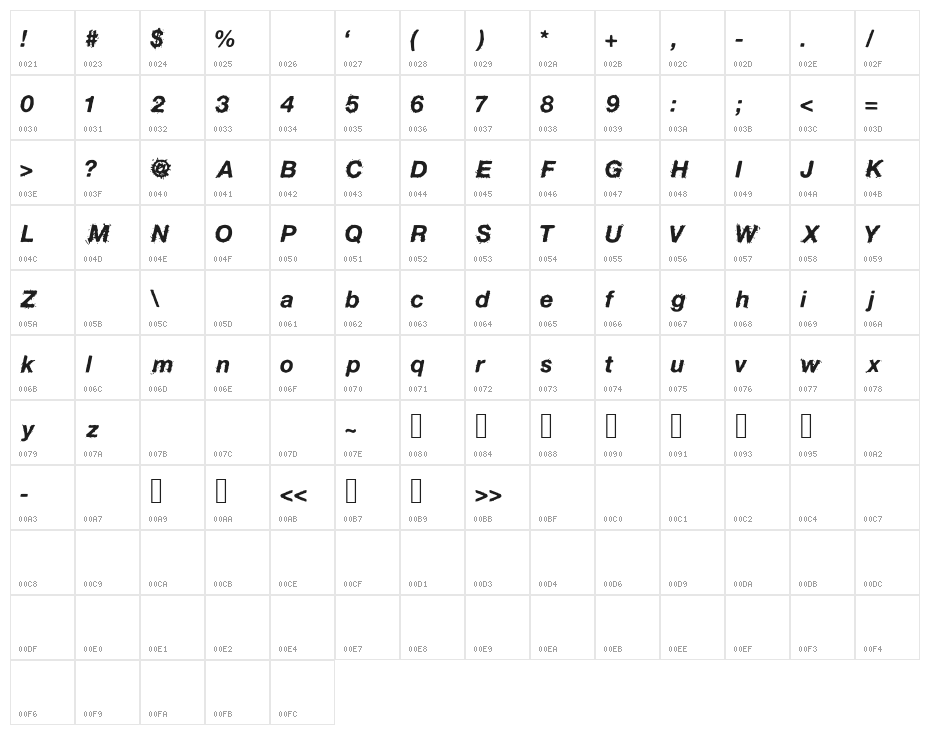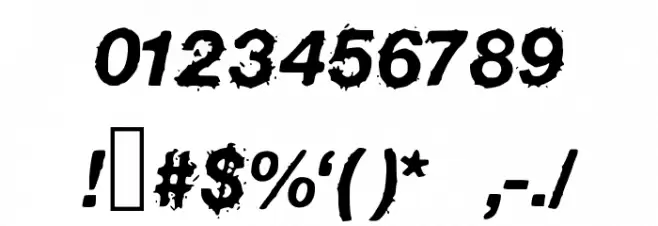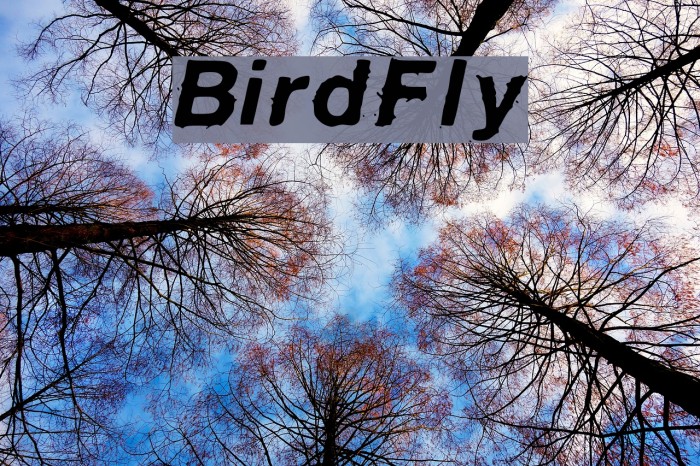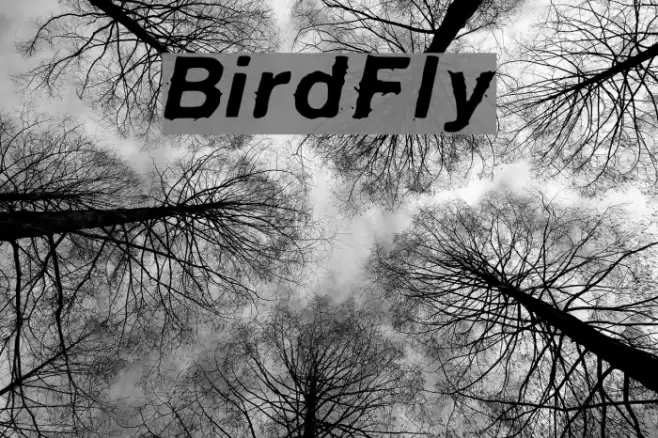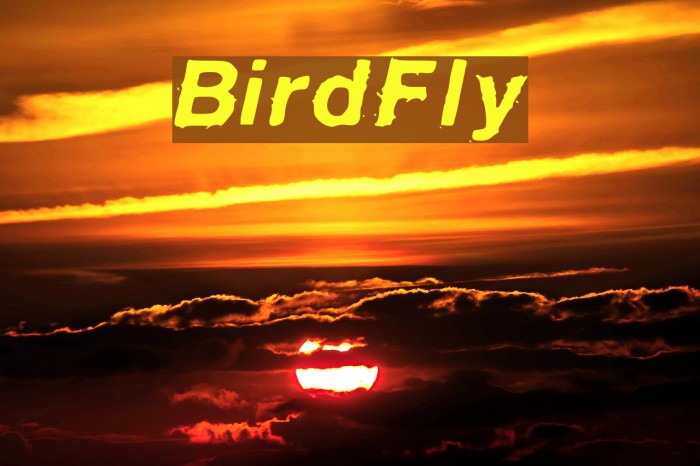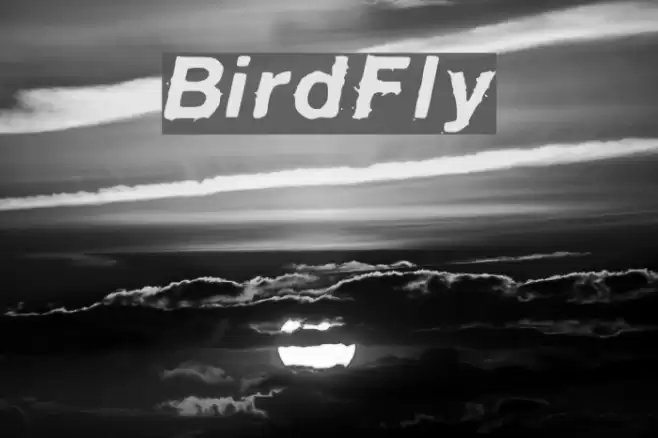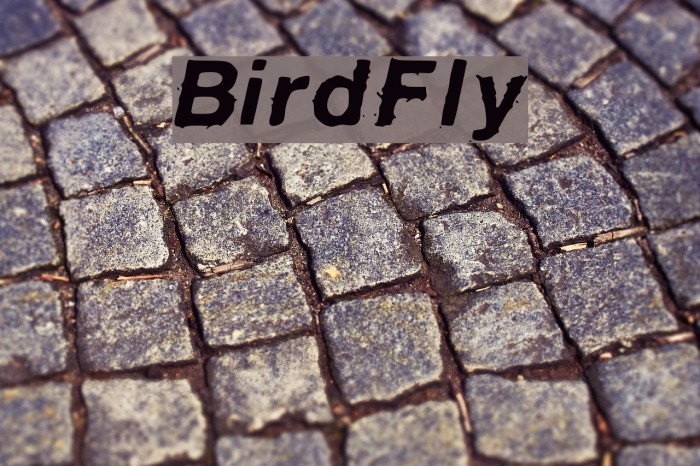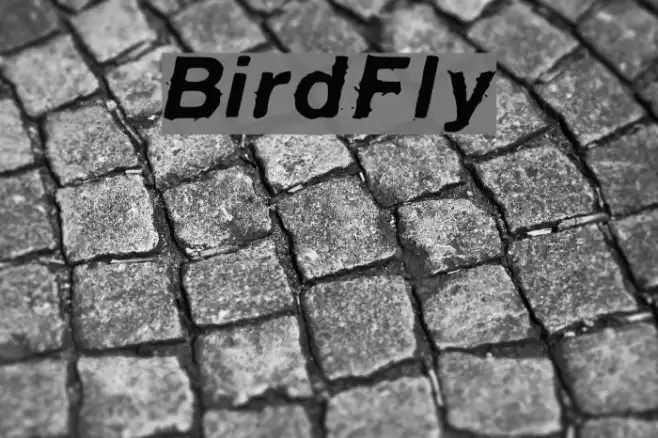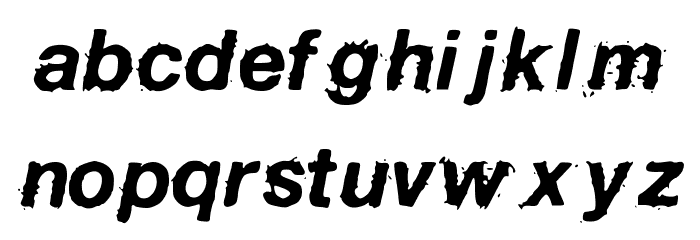
BirdFly Font
✎ Distorted Eroded
| Estilo general | Grunge, Edgy, Dynamic |
| Proyectos propuestos | Ideal for music album covers, posters, urban-themed designs, and branding that requires a bold, edgy look. |